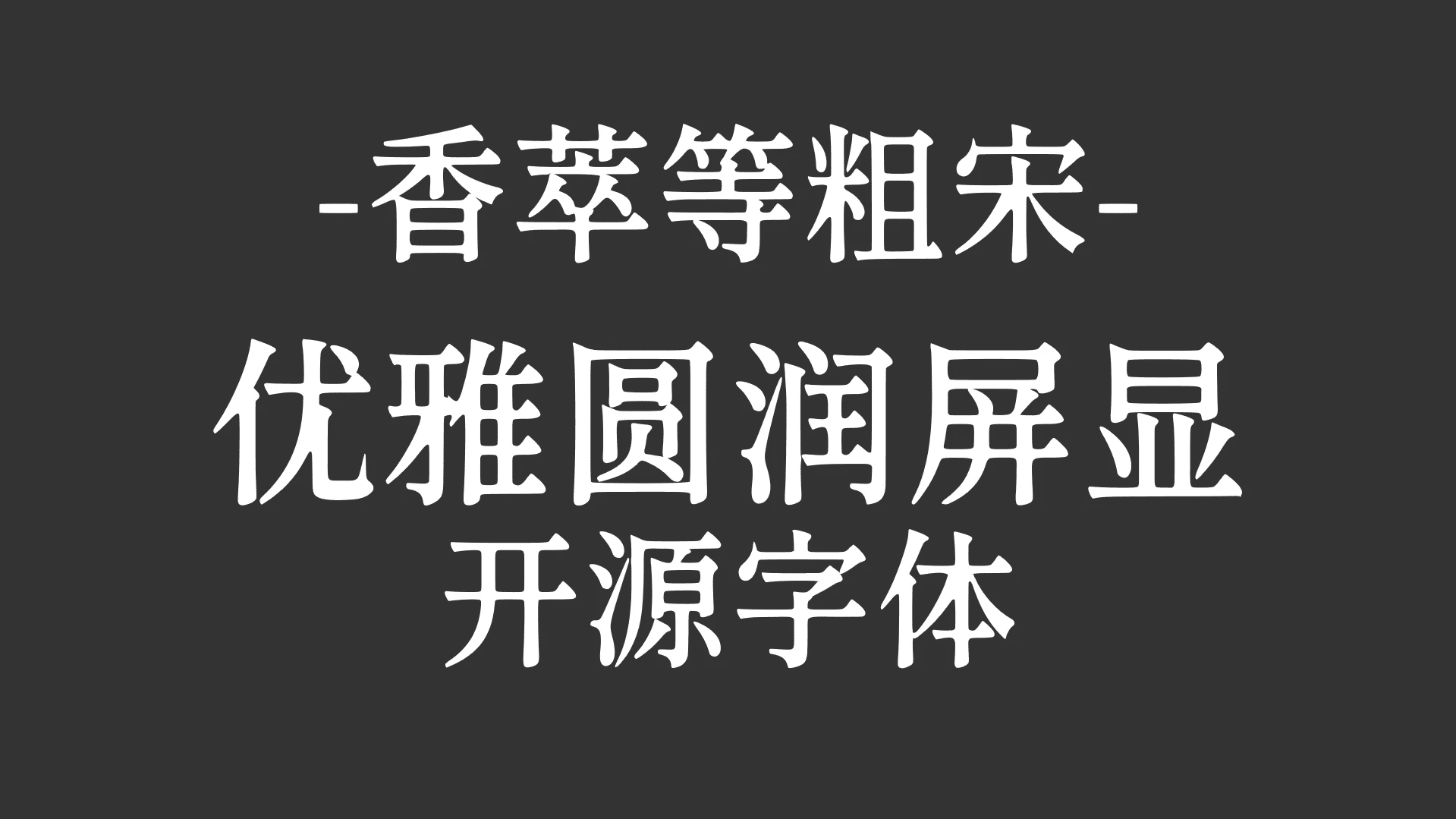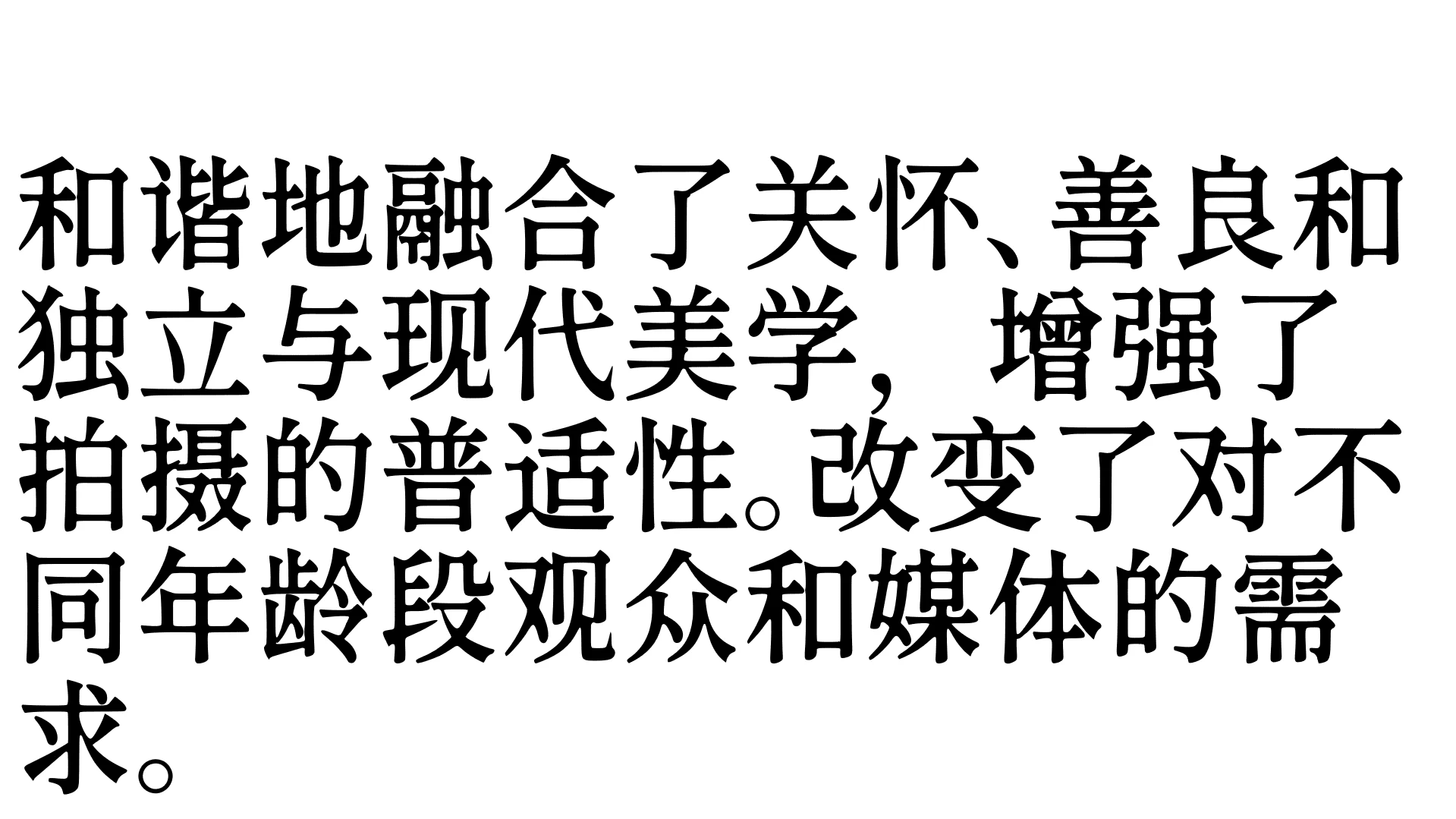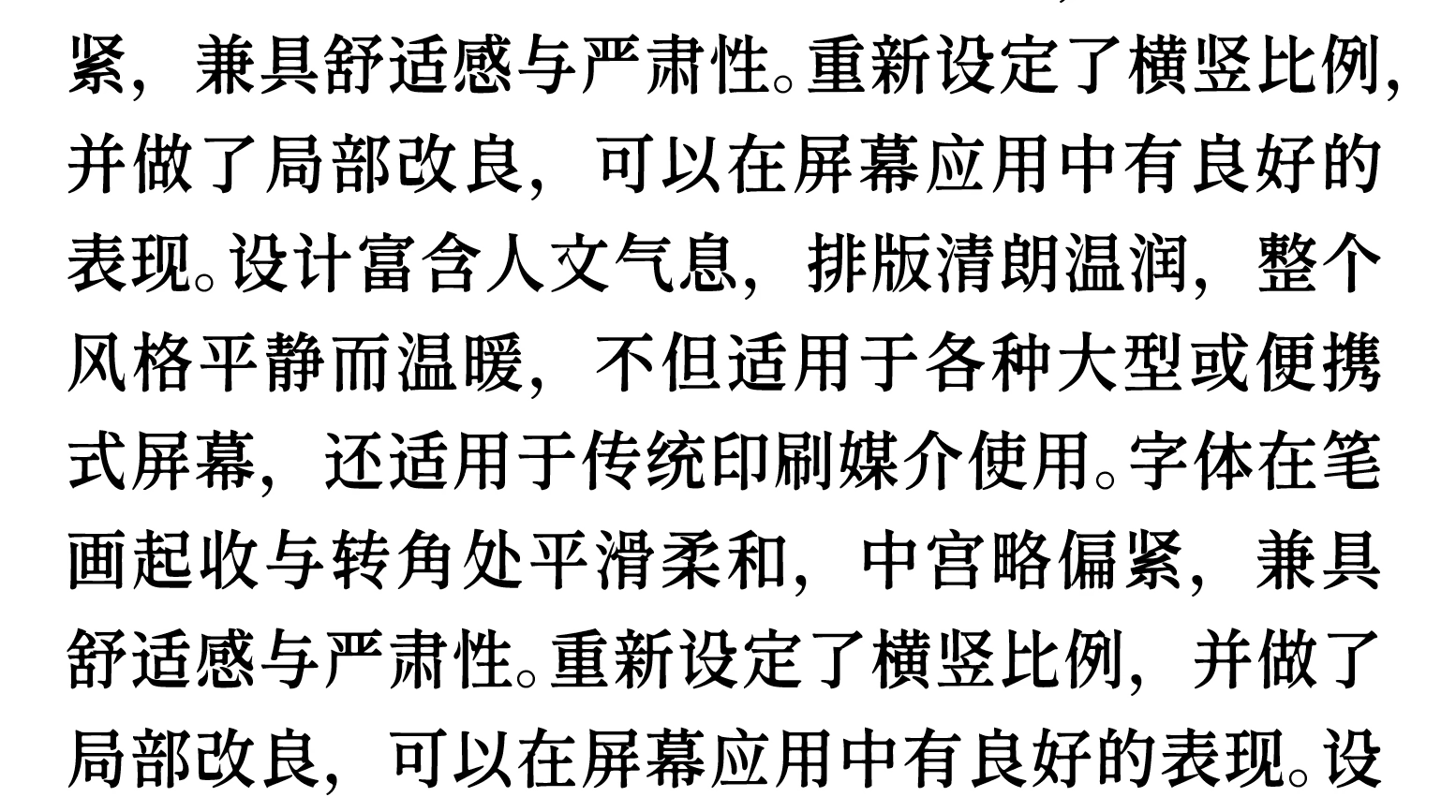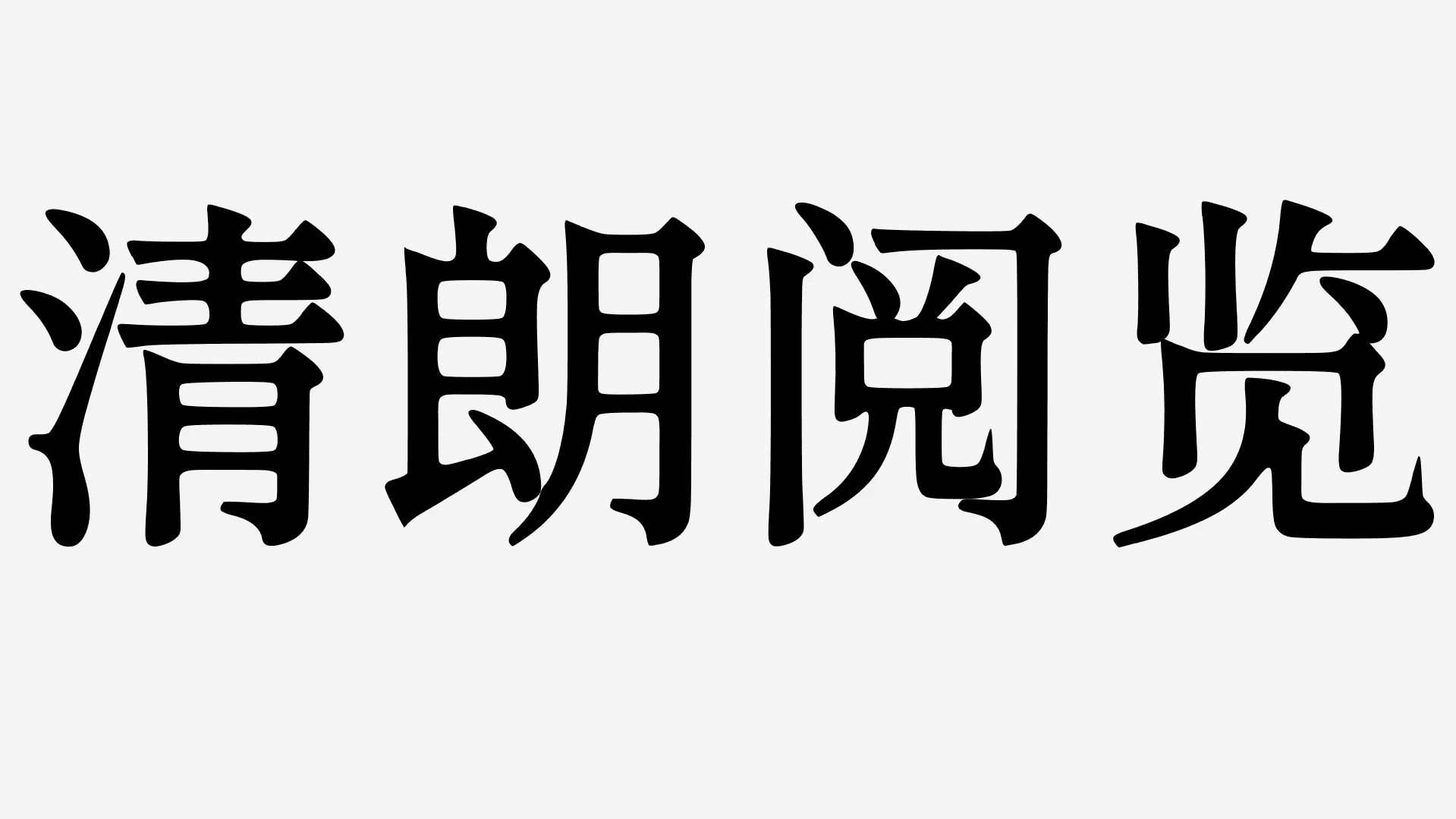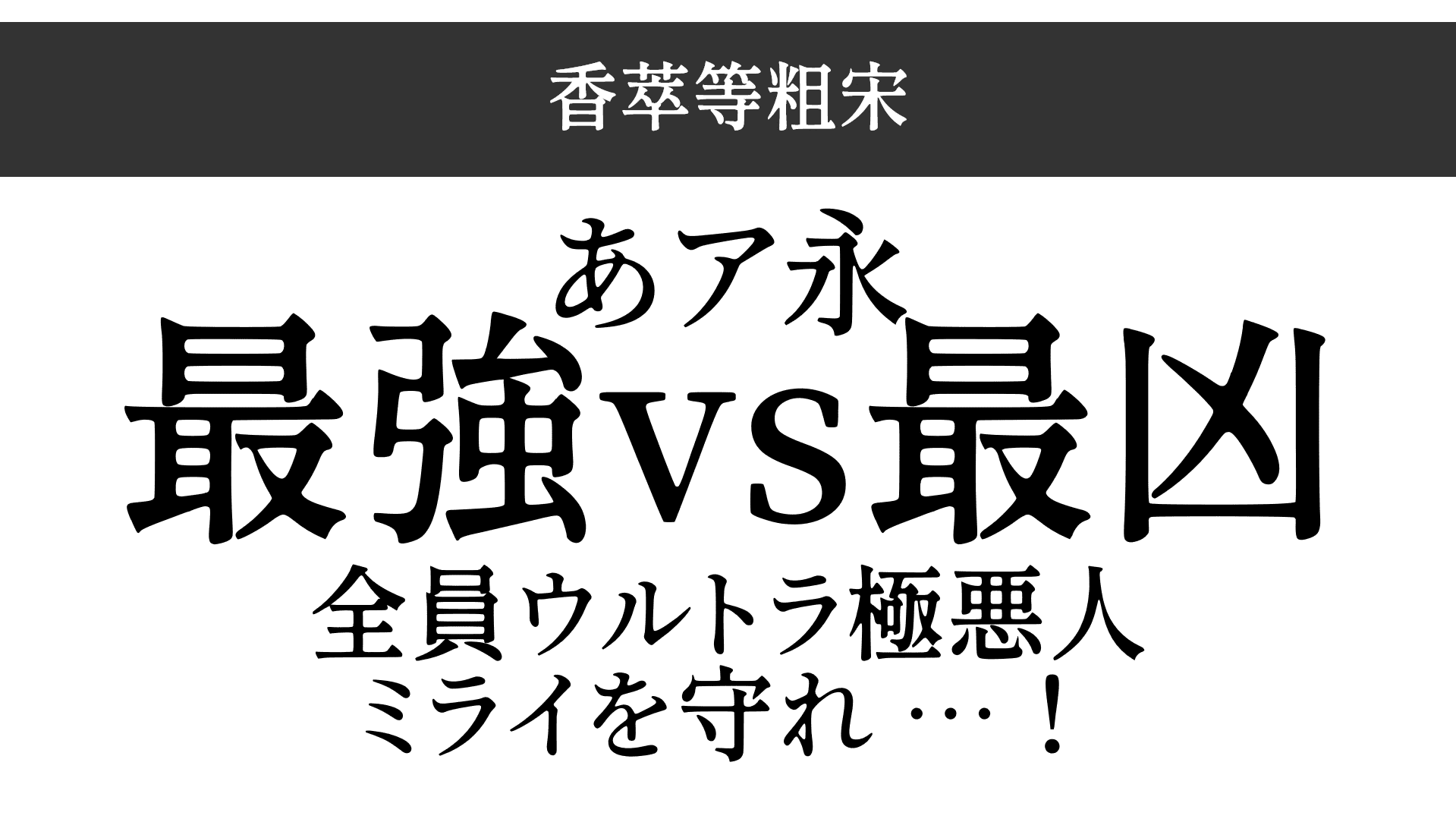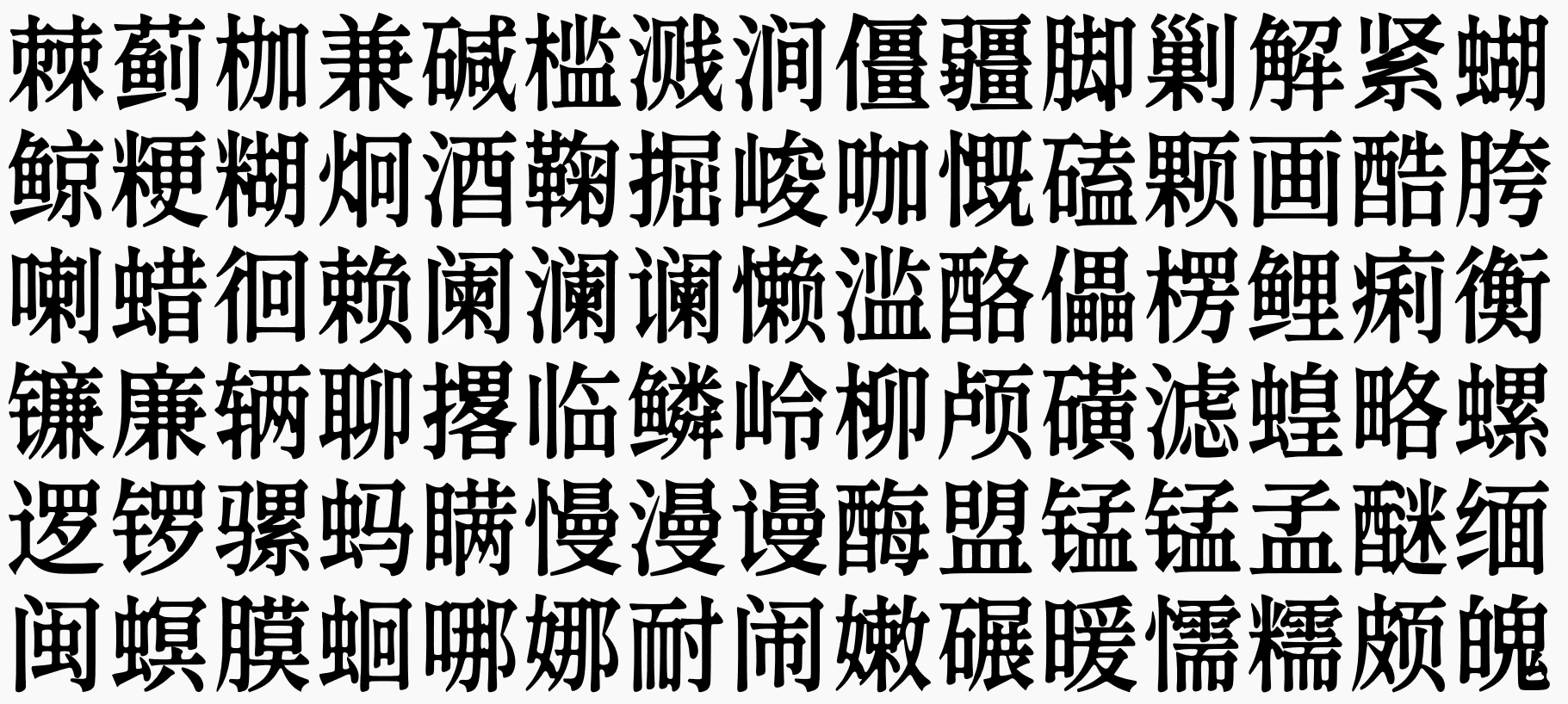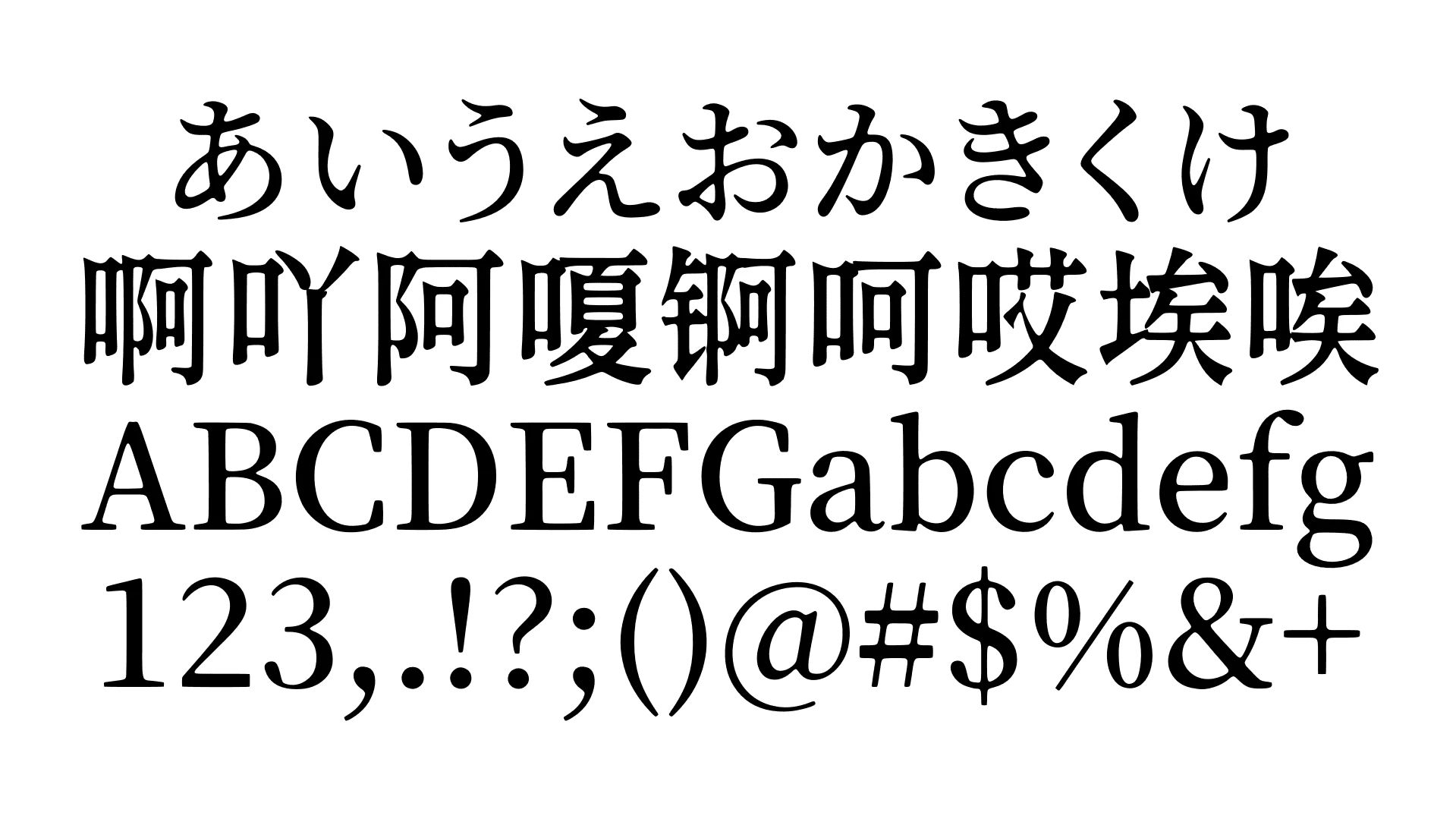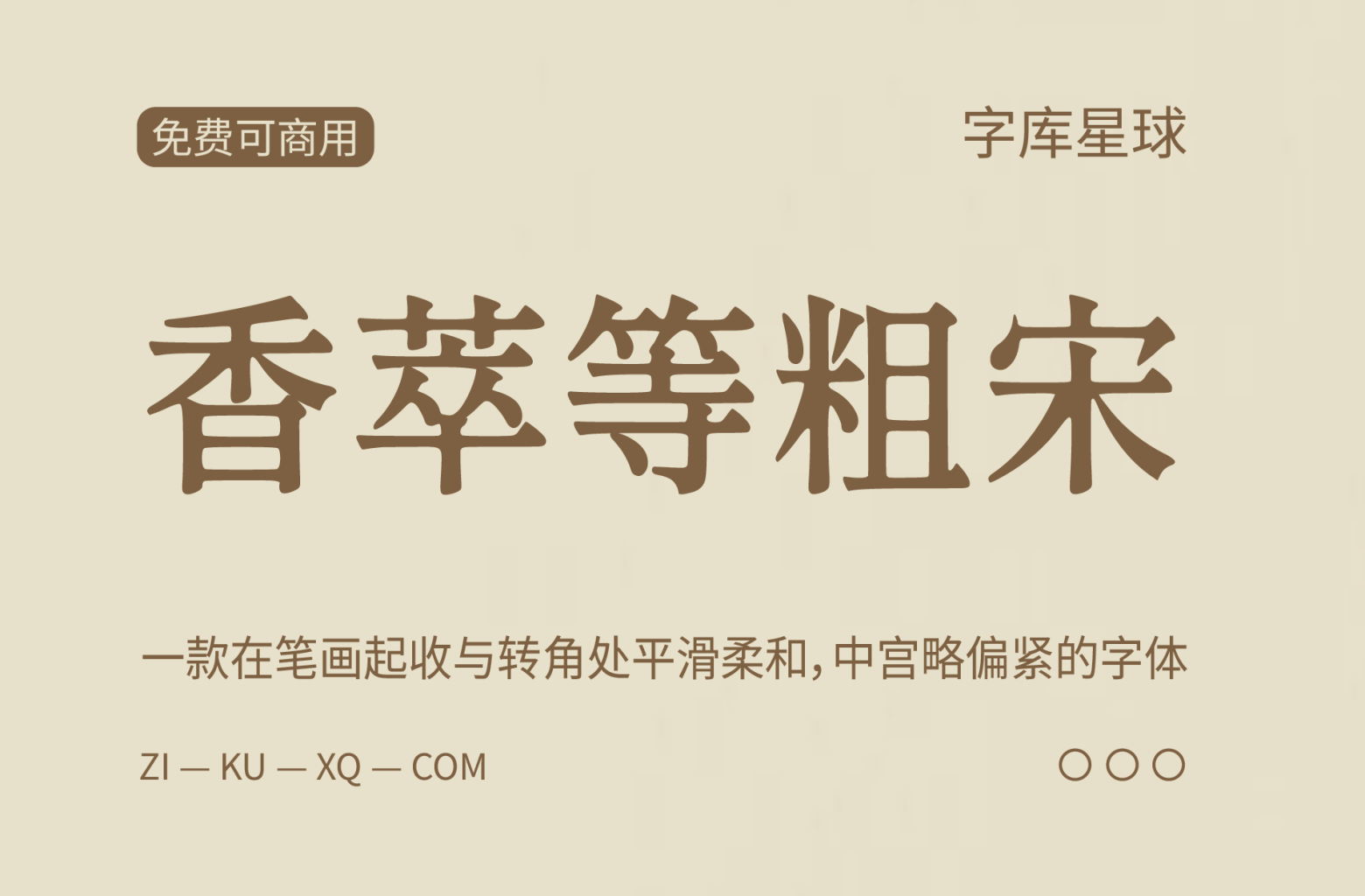
香萃等粗宋
香萃等粗宋是一款在笔画起收与转角处平滑柔和,中宫略偏紧的免费可商用字体,兼具舒适感与严肃性。重新设定了横竖比例,并做了局部改良,可以在屏幕应用中有良好的表现。
设计富含人文气息,排版清朗温润,整个风格平静而温暖,不但适用于各种大型或便携式屏幕,还适用于传统印刷媒介使用。
对于含有旧字形的汉字,除“浅残践劲茎径禅蝉惮箪莽蟒类器”等字使用中国大陆规范字形,其余使用旧字形。